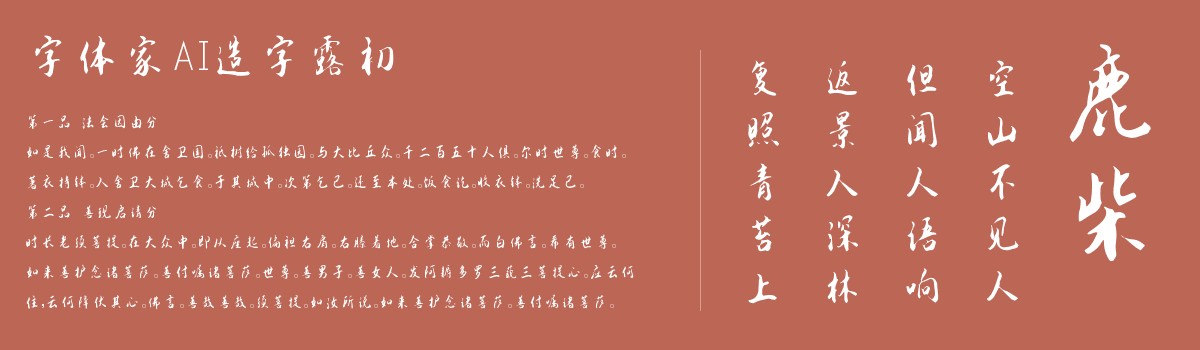
字体家AI造字露初
字体家AI造字露初是一款由字体家AI神笔造字生成的艺术字体,线条如毛笔轻扫纸面,粗细自然过渡,无生硬棱角。转角处圆润柔和,似指尖划过丝绸般顺滑。结构舒展却不失平衡,笔画带着手写的温度,能感受到书写时的从容流畅。没有刻意雕琢,透着质朴美感,像阳光下晾晒的棉纸,柔软又有筋骨,温暖亲切。适合用于一些广告标题、平面文案、海报标题、网页广告用字的编辑。